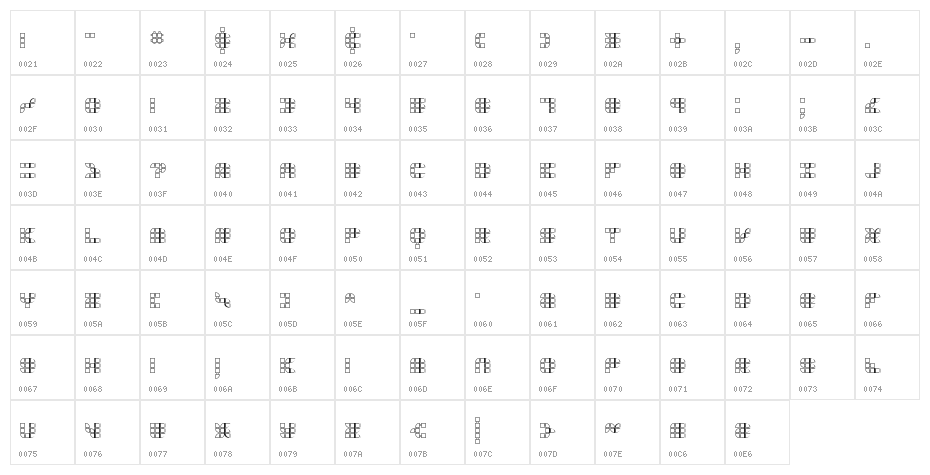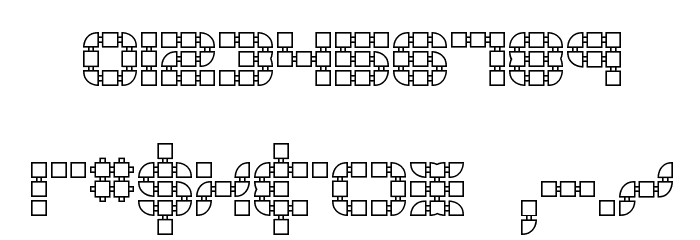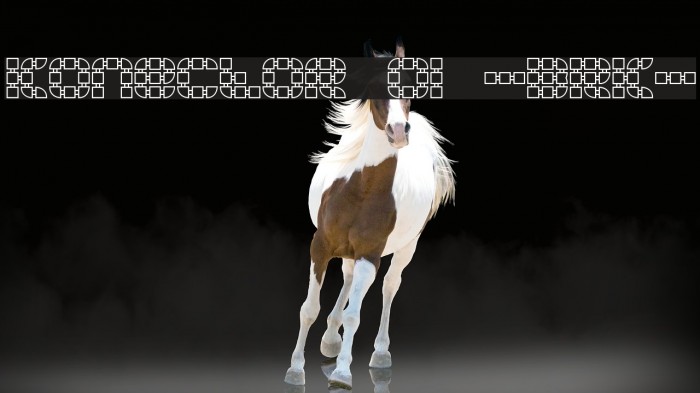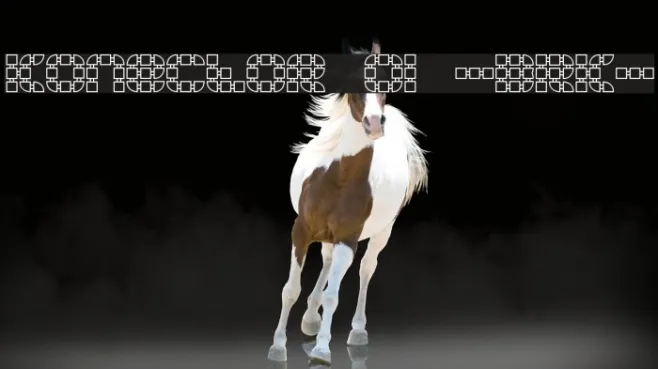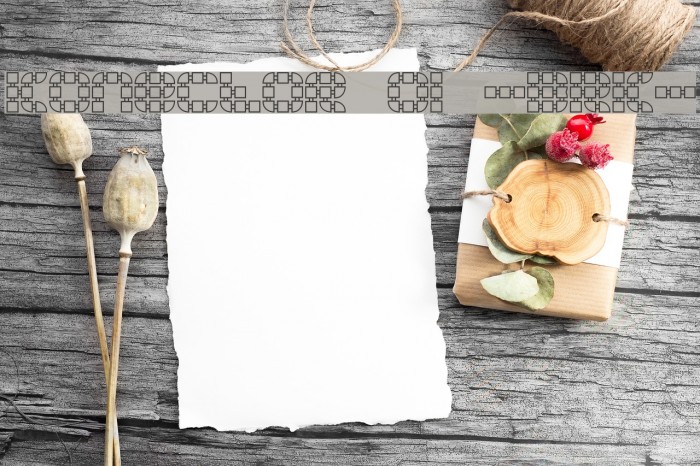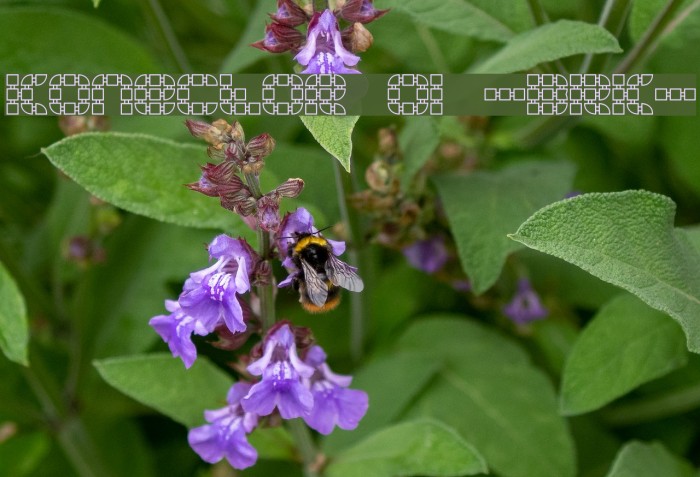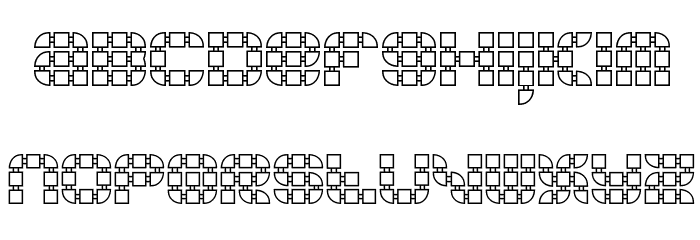
Konector O1 -BRK- Font
| Anwendungsfall | Logos, Headlines, Posters |
| Vorgeschlagene Projekte | Ideal for tech-themed designs, digital art projects, futuristic branding, and creative posters. |